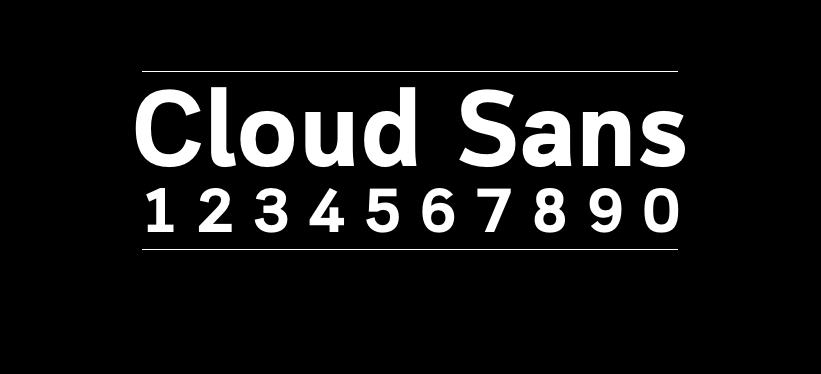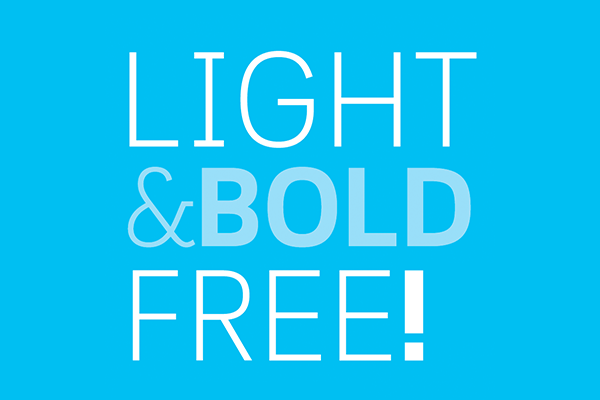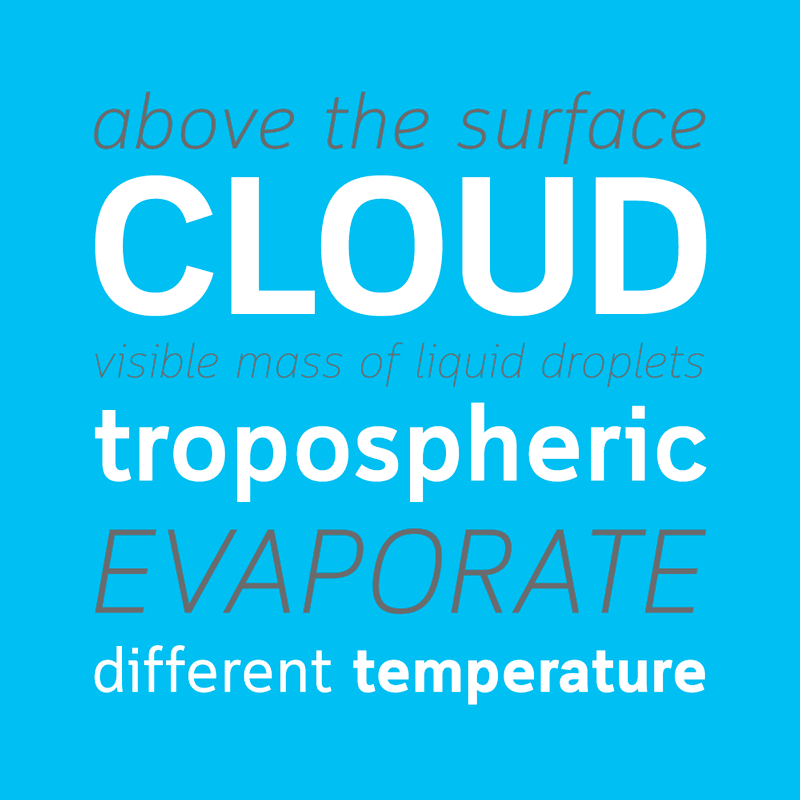
Cloud Sans
Cloud Sans是泰国设计师Typomancer创作的一款无衬线英文字体,一种人文主义的无衬线字体,带有一些怪异的结构,适用通用场合。
Cloud Sans全字体家族包含5个字重和斜体。作者免费开放其中的Light、Bold两个字型(已打包在下载文件中),并声明免费商用。如果需要更完整的字体家族,也可以通过下方的官方链接进行购买。